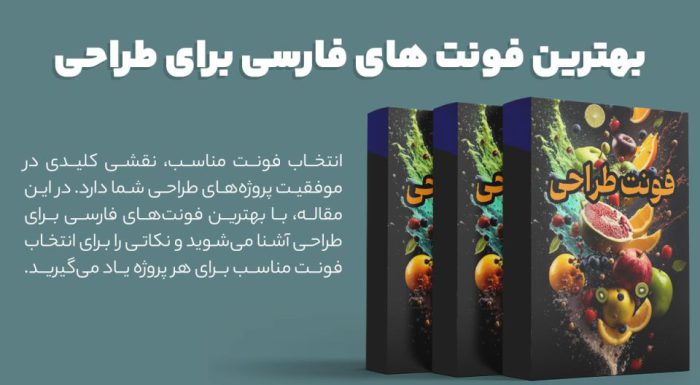
پکیج فونتهای منتخب فارسی برای طراحی
بهترین فونت های فارسی برای طراحی: پکیج ویژه پرطرفدارترین قلم ها
انتخاب فونت مناسب یکی از ارکان اساسی در دنیای طراحی گرافیک است؛ فونت درست می تواند پیام شما را به شکلی تاثیرگذار منتقل کند و بر مخاطب تاثیر بگذارد. این پکیج ویژه پاسخی به همین نیاز است. این مجموعه گلچینی از پرطرفدارترین فونت های فارسی است که از بین بیشترین خریدها انتخاب شده اند و به صورت اختصاصی برای طراحی و خلق آثار بصری جذاب گردآوری شده اند.
دانلوداین مجموعه تنوع بالایی در انواع فونت فارسی برای طراحی ارائه می دهد. شامل فونت های سریف که دارای پایه های کوچک در انتهای حروف برای خوانایی بهتر در متون بلند هستند (مانند قلم هایی نظیر یکان، وزیر، و انجمن). فونت های بدون سریف که فاقد این پایه ها بوده و ظاهری مدرن تر و مینیمال دارند، مناسب برای متون کوتاه و عنوان ها هستند (مانند ایران سنس، شبنم، و دانا). فونت های دست نویس با ظاهری شبیه به خط خوشنویسی، حس صمیمیت را القا کرده و برای پروژه های خلاقانه کاربرد دارند (مانند لیلا، آینه دار، و نستعلیق). و در نهایت، فونت های نمایش (Display) که برای جلب توجه و ایجاد تاثیر بصری قوی در عنوان ها و لوگوها طراحی شده اند (مانند استعاره، شاه دخت، و کوفی). این آرشیو با پوشش این سبک های اصلی، قلم های مناسبی برای هر بخش از طراحی ارائه می دهد.
در انتخاب فونت باید به خوانایی در اندازه های مختلف، ایجاد سلسله مراتب بصری با استفاده از وزن ها و اندازه های متفاوت قلم، و تناسب فونت با فضا و نوع پروژه طراحی توجه کرد. قلم های موجود در این پکیج با در نظر گرفتن این نکات انتخاب شده اند تا ابزاری مؤثر برای طراحان باشند.
کاربردهای پکیج بهترین فونت های طراحی در پروژه های مختلف
پکیج بهترین فونت های فارسی برای طراحی با ارائه تنوع سبک های محبوب و باکیفیت، کاربردهای گسترده ای در انواع پروژه های طراحی گرافیک دارد. این مجموعه شامل قلم های مناسب برای طراحی وب سایت (به خصوص برای متون اصلی و عنوان ها)، طراحی لوگو (با گزینه های متنوع سریف، بدون سریف و نمایشی)، و طراحی پوستر (با فونت های نمایشی قدرتمند) می باشد.